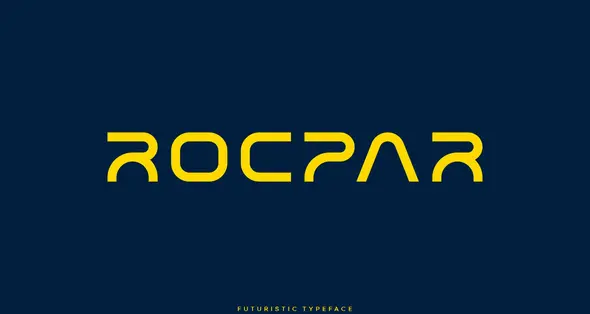
• Rocpar - Modern Futuristic Typeface
Rocpar یک فونت نمایشی مینیمال و مدرن منحصر به فرد است که کلاس خود را تعریف می کند. Rocpar برای اهداف نمایشی و برندینگ طراحی شده است و این فونت می تواند انتخابی عالی برای ساخت لوگو، برندینگ، عنوان، تبلیغات دیجیتال، مواد بازاریابی برای وب و چاپ و همچنین هر نوع طراحی مینیمال باشد.
Rocpar is an unique minimal & modern display typeface that defines a class of it's own. Rocpar is dedicated for display and branding purposes, where this typeface can be a perfect choice for creating logotype, branding, headline, digital ads, marketing material for web & print as well as any type of minimal design.